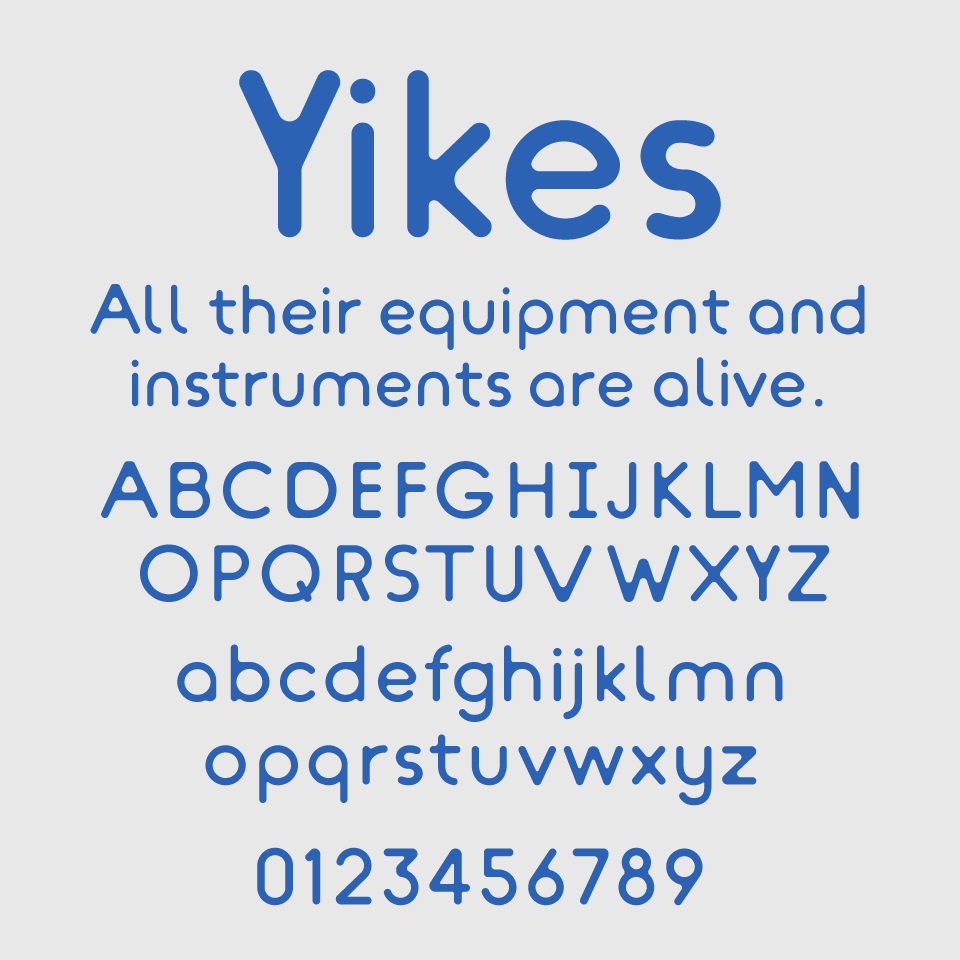
Yikesフォントは、丸みを帯びたラインと広めの字間が特徴的な、ユーモアと親しみやすさを持ったサンセリフ体です。角をなくした文字形状が柔らかさと安心感を与え、絵本や子ども向けコンテンツにぴったりのデザインです。
文字の均一な太さと簡潔なシルエットは、明快で視認性も良好。遊び心のある印象を保ちつつも整然としたバランス感があり、やさしい雰囲気の中にも信頼感のあるフォントです。